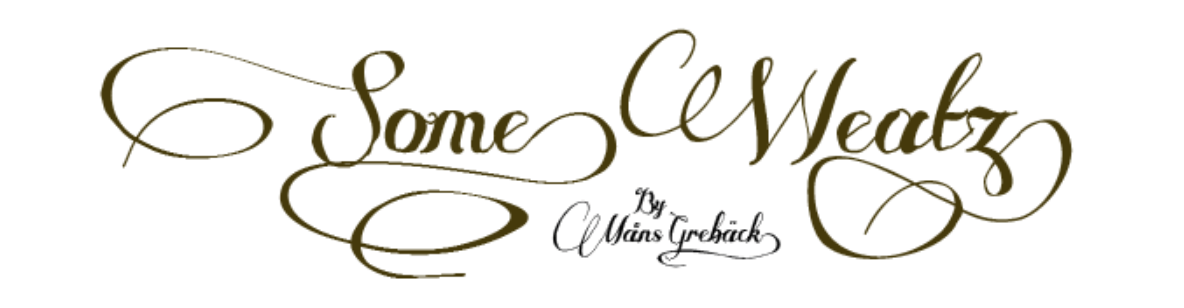
1. Rottarity Feminine
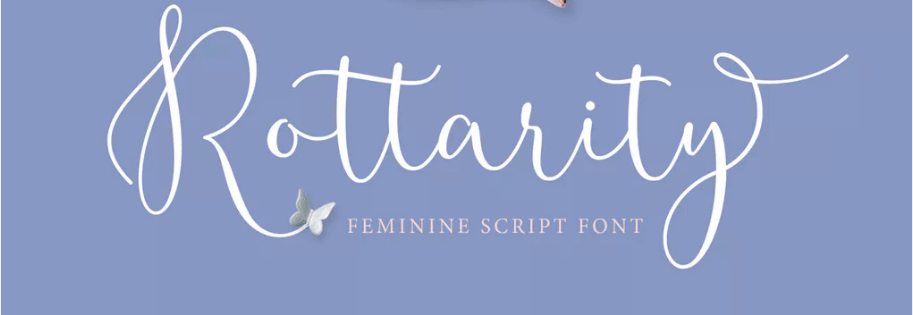
En primer lugar, este guión ligero y bonito presenta elegantes swashes y es adaptable para varios usos. Ideal para invitaciones y tarjetas de felicitación, Rottarity Feminine agrega clase a su contenido sin ser abrumador.
2. Puerto
Un aspecto de caligrafía da la impresión de que se ha invertido mucho tiempo en su contenido, lo que hace que las fuentes como Harbour se sientan como opciones de alta gama. Esta fuente también es un poco más angular que algunas de las otras entradas en esta lista, lo que la distingue de los muchos scripts redondeados que están disponibles.
3. Guión de Bellanie
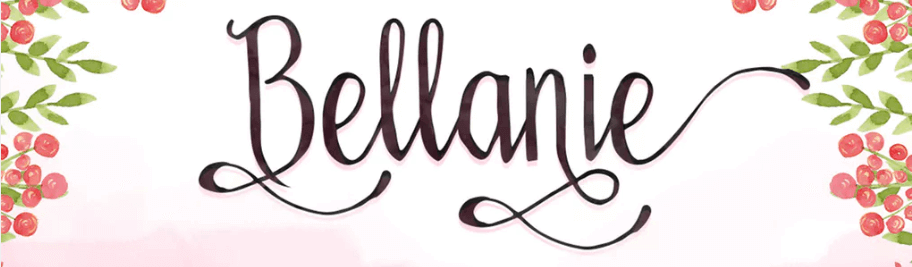
A veces, desea una fuente que coincida con el tono de su evento, pero que no se robe por completo el espectáculo. Bellanie Script es una fuente que utiliza caracteres sutiles y colas largas para producir un encanto más tranquilo. Por lo tanto, es una buena opción para darle a su contenido un toque único sin abrumar su mensaje.
4. Cielo helado
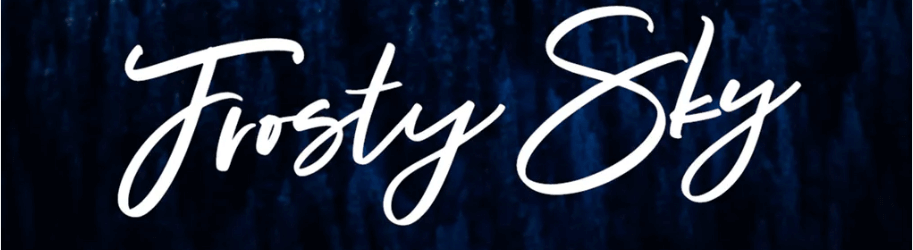
Esta fuente manuscrita le da un toque personal a los títulos y encabezados. Sus amplias letras mayúsculas hacen declaraciones audaces y están diseñadas para impresionar.
5. Cítricos
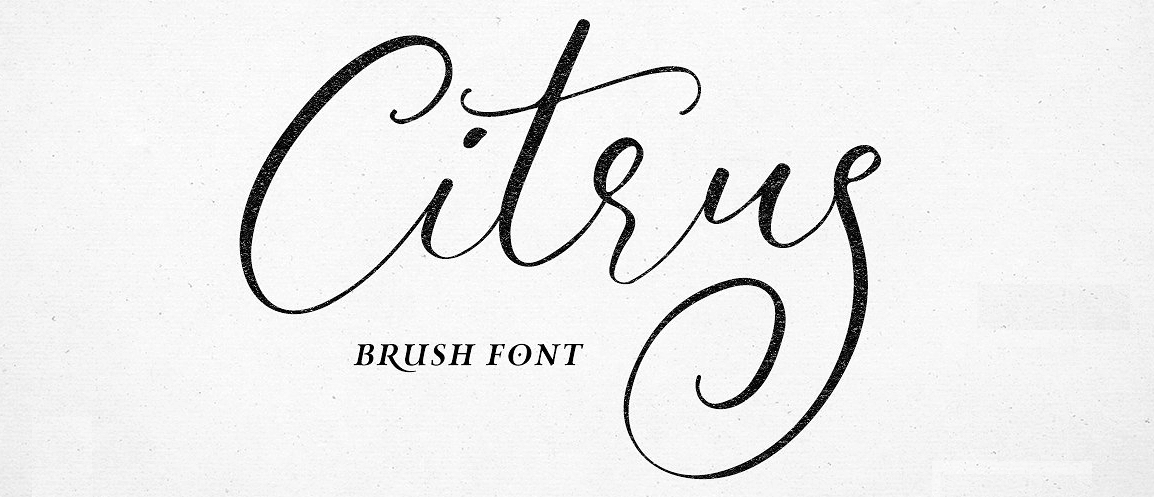
Este impresionante guión se enorgullece de una apariencia de elegancia. Citrus ofrece caracteres redondeados que son muy atractivos, pero aún así son altamente legibles (a diferencia de muchos otros guiones 'loopy').
6. Monalisa
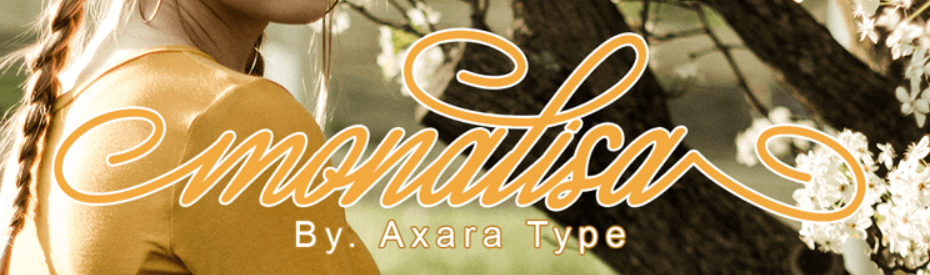
Si está buscando un guión compacto, puede probar Monalisa. Sus caracteres estrechos no ocuparán demasiado espacio en la página, pero las letras no son tan delgadas que harán que su texto sea difícil de descifrar.
7. Script de Marchy
Para un tono más divertido, puede probar Marchy Script. Con una línea de base danzante y tallos ligeramente curvados, esta fuente crea títulos y títulos divertidos que atraen la atención del visitante.
8. Rosa de Baltimore
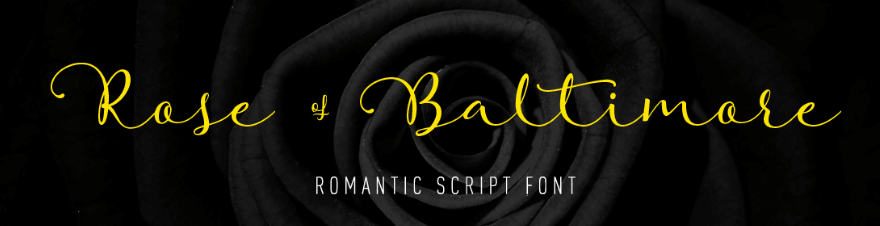
Este hermoso guión le permite incorporar mucho espacio en blanco en su diseño. Considerado "romántico" por su diseñador, Rose of Baltimore es perfecto para cualquiera que desee brindar a su sitio una sensación de calidez y familiaridad.
9. Gaby
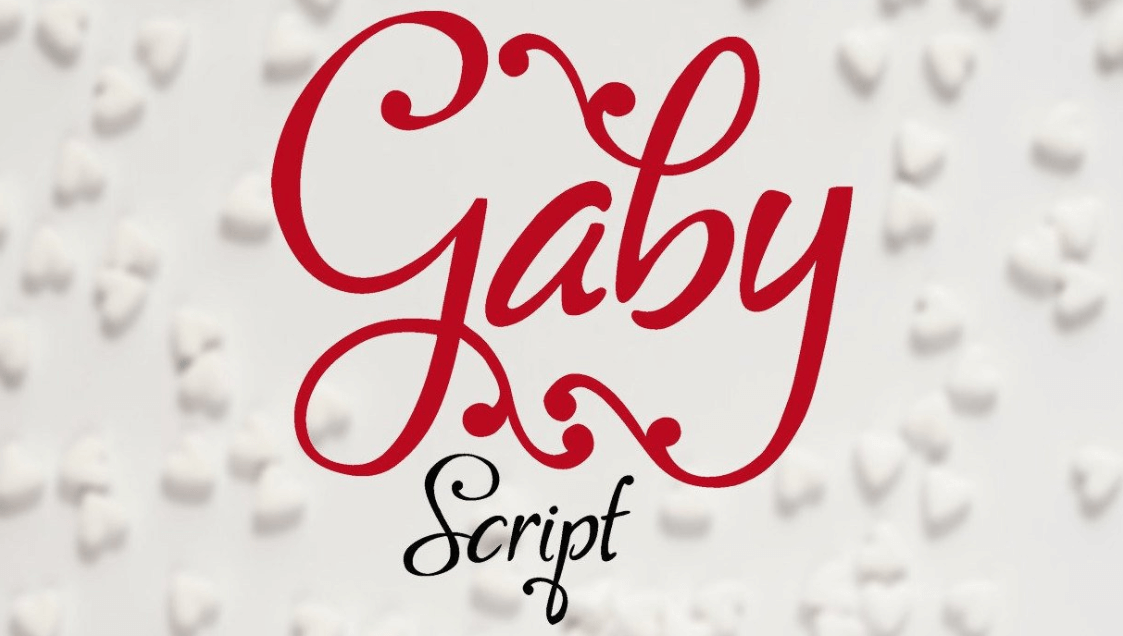
Los motivos decorativos adornados con pequeños detalles redondos hacen que esta fuente simple se destaque. Gaby es elegante sin ser agresivo al respecto, dejando que tu contenido hable la mayor parte del tiempo.
10. Galiano
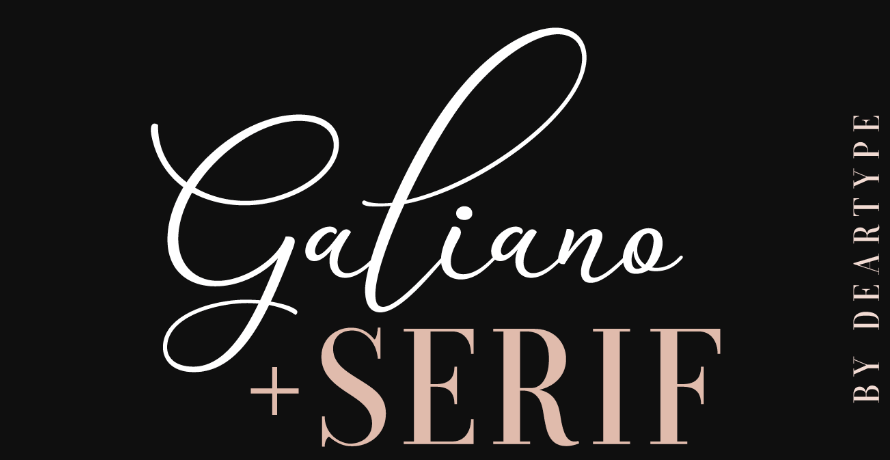
La fuente Galiano presenta ascendentes y descendentes grandes y en bucle, que seguramente llamarán la atención de su audiencia. Otra opción que hace un uso inteligente del espacio en blanco, Galiano es ideal para promover eventos formales de lujo.
11. PF Champion Script Pro
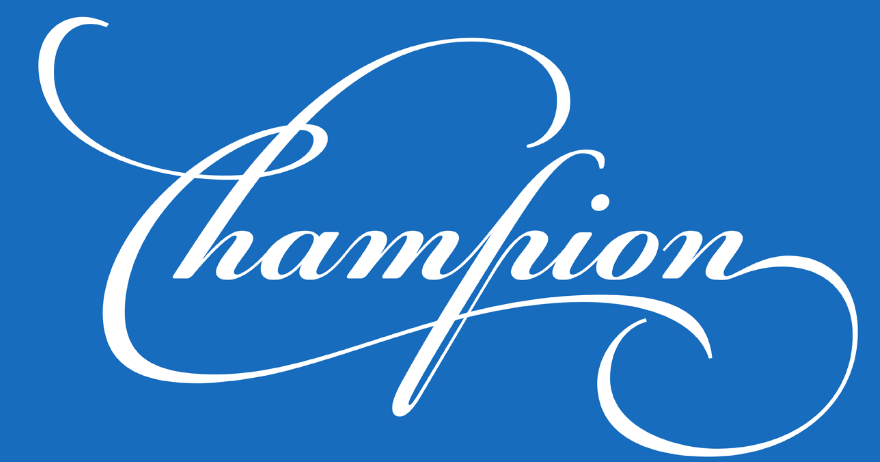
Si quieres hacer todo lo posible y realmente captar la atención de todos, el ornamentado PF Champion Script Pro puede hacer el trabajo. Con sus lujosos guirnaldas y un aire regio, esta fuente es sorprendente y memorable.
12. Qaskin
Maravillosamente elegante y fácil de leer, Qaskin es una excelente opción para cualquier ocasión. Este script con clase se siente fresco y atractivo, pero al mismo tiempo no desviará la atención del resto del contenido de su sitio.
Mientras que los guiones rizados dan una sensación de lujo, los adornos decorativos más simples pueden verse igual de elegantes cuando se usan bien. Ya sea que desee hacer una declaración audaz con PF Champion Script Pro, o seguir una ruta más sutil con una fuente como Bellanie Script o Asian Skyline, hay una fuente adecuada para cada ocasión especial.